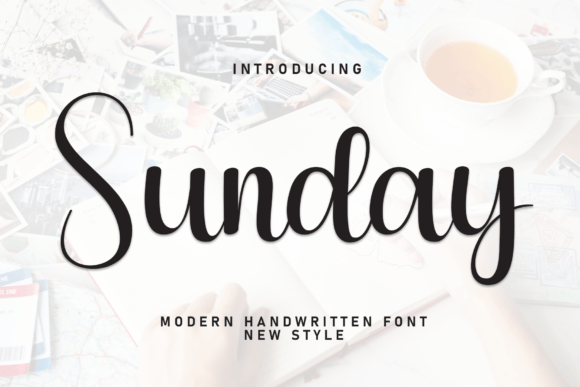
Sunday Font
منتج “خط الأحد” هو تصميم رقمي فريد يقدم لك خطًا أنيقًا ومميزًا مثاليًا للاستخدام في المشاريع الإبداعية. يتميز هذا الخط بأسلوبه العصري والمرن، مما يجعله مناسبًا لبطاقات الدعوة، الشعارات، أو أي تصميم يحتاج لمسة فنية. سهل الاستخدام، يضيف لمسة جمالية إلى أعمالك ويساعدك على التعبير عن إبداعك بأسلوب مميز!